การเลือกใช้อักษรพิเศษหรือฟอนต์ในงานออกแบบ เป็นหนึ่งในกลยุทธ์ด้านการสร้างแบรนด์ดิ้งที่ทุกธุรกิจไม่ควรพลาด เช่นเดียวกับการเพิ่มเติมความโดดเด่นให้แก่งานออกแบบด้วยสีสันหลากหลายเฉด โดยเฉพาะกับการใช้ฟอนต์ภาษาอังกฤษสวย ๆ หรือฟอนต์อังกฤษที่มีลักษณะและให้ความรู้สึกเหมาะสมกับแบรนด์ ADCHARIYA จึงได้รวบรวม 20 ฟอนต์ภาษาอังกฤษหลากหลายสไตล์มาฝากกัน และแต่ละฟอนต์สามารถดาวน์โหลดไปใช้งานฟรีได้เลย
1. Serendipity
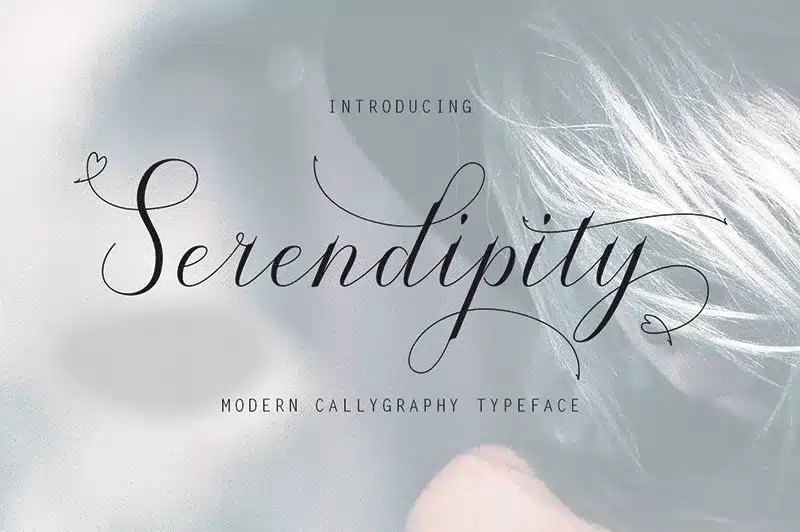
Serendipity เป็นฟอนต์ภาษาอังกฤษที่มีเสน่ห์ด้วยลายเส้นที่นุ่มนวลและเรียบง่าย การออกแบบที่เน้นความสบายตาและความเป็นธรรมชาติ ทำให้เหมาะกับงานออกแบบที่ต้องการความผ่อนคลายและความสบาย ๆ เช่น ร้านสปา ผลิตภัณฑ์บำรุงผิว หรือร้านอาหารเพื่อสุขภาพ
2. Honeydays
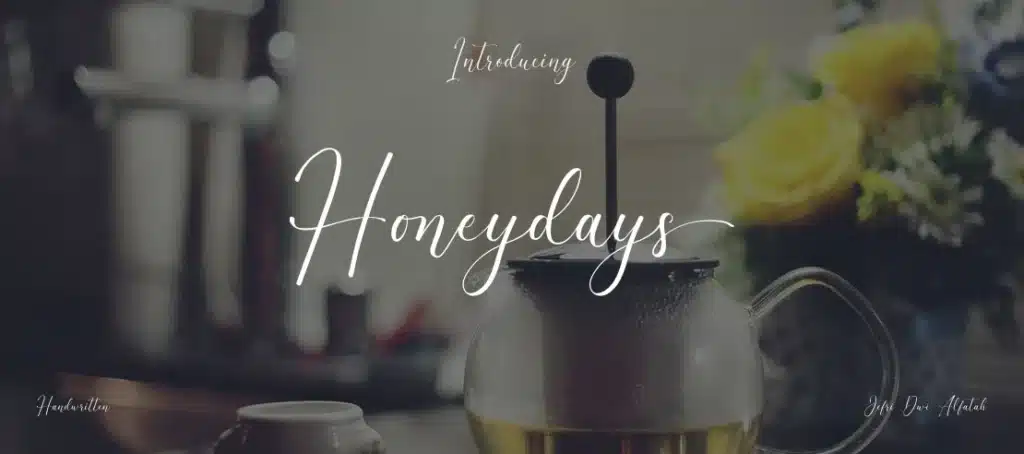
Honeydays เป็นฟอนต์ภาษาอังกฤษแบบ Calligraphy ที่มีความอ่อนหวานและสง่างาม โดดเด่นด้วยลายเส้นที่บางเบาและลื่นไหล สร้างความรู้สึกอบอุ่นและเป็นกันเอง เหมาะสำหรับงานออกแบบที่ต้องการสื่อถึงความรักและความอ่อนโยน เช่น การ์ดแต่งงาน การ์ดอวยพร หรือโลโก้ร้านดอกไม้
3. Butler
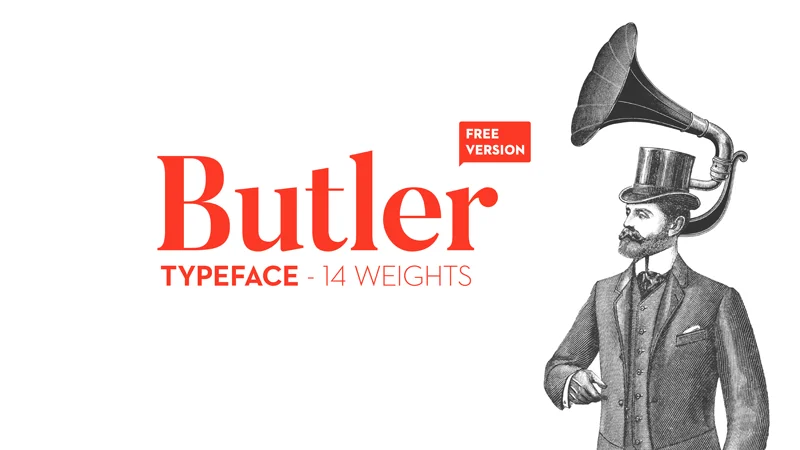
Butler เป็นฟอนต์อังกฤษที่นำเสนอความเรียบหรูผ่านการออกแบบสไตล์ Modern Serif ที่มีความสมดุลระหว่างความคลาสสิกและความร่วมสมัย ด้วยลายเส้นที่คมชัดและมีเอกลักษณ์ ทำให้เหมาะกับการใช้งานในหลากหลายรูปแบบ โดยเฉพาะงานที่ต้องการความน่าเชื่อถือและความเป็นมืออาชีพ
4. Pacifico
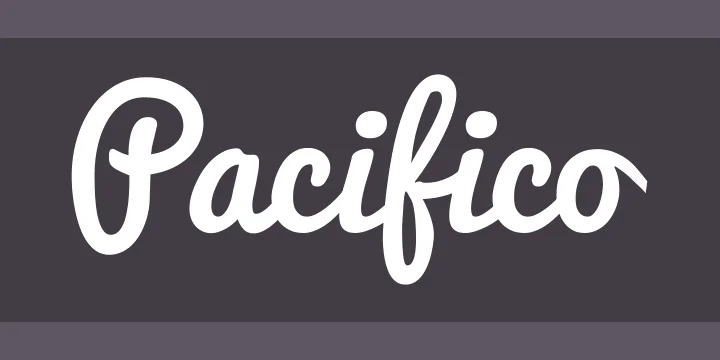
Pacifico เป็นฟอนต์อังกฤษที่ได้รับแรงบันดาลใจจากการเขียนด้วยพู่กันแบบย้อนยุค มาพร้อมกับความสนุกสนานและมีชีวิตชีวา ด้วยลายเส้นที่หนาแน่นและมีจังหวะที่สนุก เหมาะสำหรับงานออกแบบที่ต้องการความสดใสและความเป็นกันเอง เช่น ร้านอาหาร คาเฟ่ หรือธุรกิจท่องเที่ยว
5. Peich Typeface
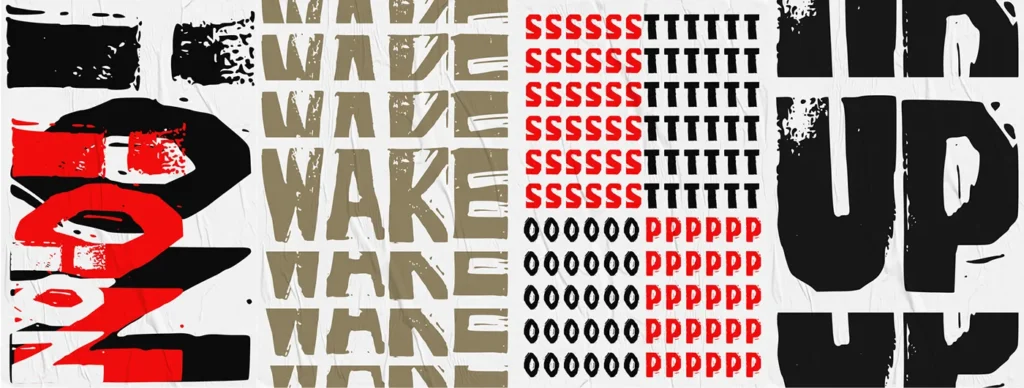
Peich Typeface เป็นฟอนต์ภาษาอังกฤษที่สร้างความโดดเด่นด้วยความหนาและความแข็งแกร่งของตัวอักษร ผสมผสานกลิ่นอายความวินเทจเข้ากับความทันสมัยได้อย่างลงตัว เหมาะสำหรับงานออกแบบที่ต้องการสื่อถึงความแข็งแกร่งและความมั่นคง เช่น โลโก้แบรนด์สปอร์ต ป้ายโฆษณา หรือแพ็กเกจจิงสินค้าสำหรับผู้ชาย
6. Sacramento
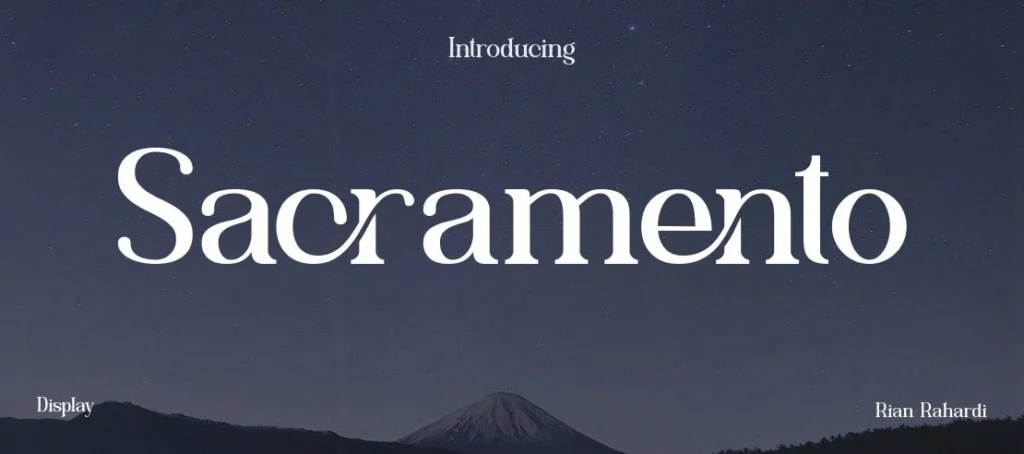
Sacramento ฟอนต์ภาษาอังกฤษตัวเขียนที่ได้แรงบันดาลใจจากการเขียนด้วยลายมือแบบคลาสสิกยุค 50-60 ผสมผสานความสวยงามของลายเส้นที่ลื่นไหลเข้ากับความเป็นธรรมชาติได้อย่างลงตัว เหมาะสำหรับงานออกแบบที่ต้องการความอ่อนช้อยและความเป็นศิลปะ เช่น งานแต่งงาน โลโก้ร้านดอกไม้ หรือการเขียนการ์ดอวยพร
7. Hello Night
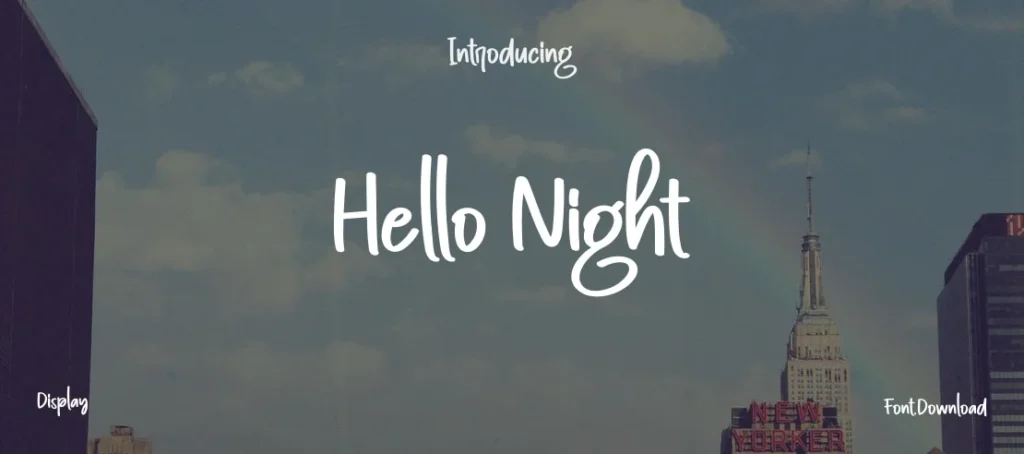
Hello Night เป็นฟอนต์อังกฤษตัวเขียนที่ผสมผสานความวินเทจเข้ากับความทันสมัยได้อย่างลงตัว ด้วยลายเส้นที่มีความพลิ้วไหวและสง่างาม เหมาะสำหรับงานออกแบบที่ต้องการความคลาสสิกแต่ไม่ดูเชย เช่น แพ็กเกจจิงสินค้าพรีเมียม หรือการ์ดเชิญร่วมงานต่าง ๆ
8. CLATTERING
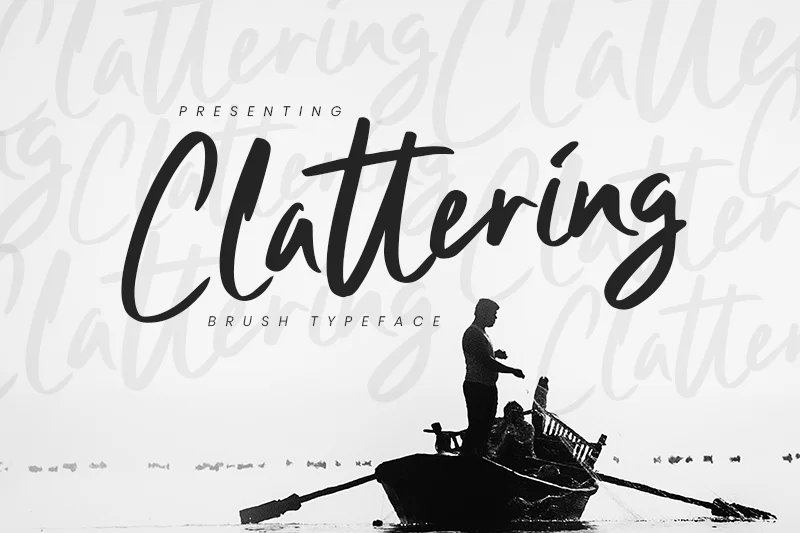
CLATTERING เป็นฟอนต์ภาษาอังกฤษสไตล์ Brush Script ที่โดดเด่นด้วยลายเส้นแบบสีน้ำที่ดูเป็นธรรมชาติและมีชีวิตชีวา ให้ความรู้สึกศิลปะและความคิดสร้างสรรค์ผ่านการไล่น้ำหนักของเส้นที่แตกต่างกัน เหมาะสำหรับงานออกแบบที่ต้องการความเป็นศิลปะ เช่น แกลเลอรี่ ร้านกาแฟ หรือสตูดิโอออกแบบ
9. Wild Youth
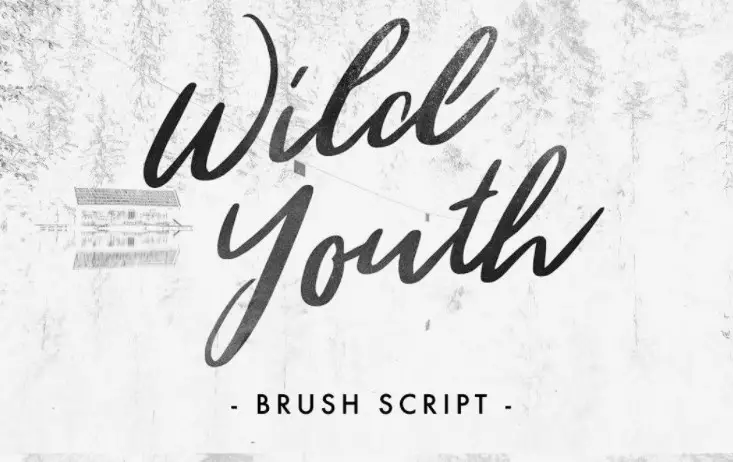
Wild Youth ฟอนต์อังกฤษที่ได้รับแรงบันดาลใจจากธรรมชาติและการผจญภัย สะท้อนผ่านลายเส้นที่ดูเป็นธรรมชาติแต่แฝงความเท่และทันสมัย เหมาะสำหรับแบรนด์ที่ต้องการสื่อถึงความเป็นออร์แกนิค อิสระ และการใช้ชีวิตกลางแจ้ง ไม่ว่าจะเป็นร้านอาหารเพื่อสุขภาพ ผลิตภัณฑ์ออร์แกนิค หรืออุปกรณ์แคมปิ้งก็ตาม
10. Lato
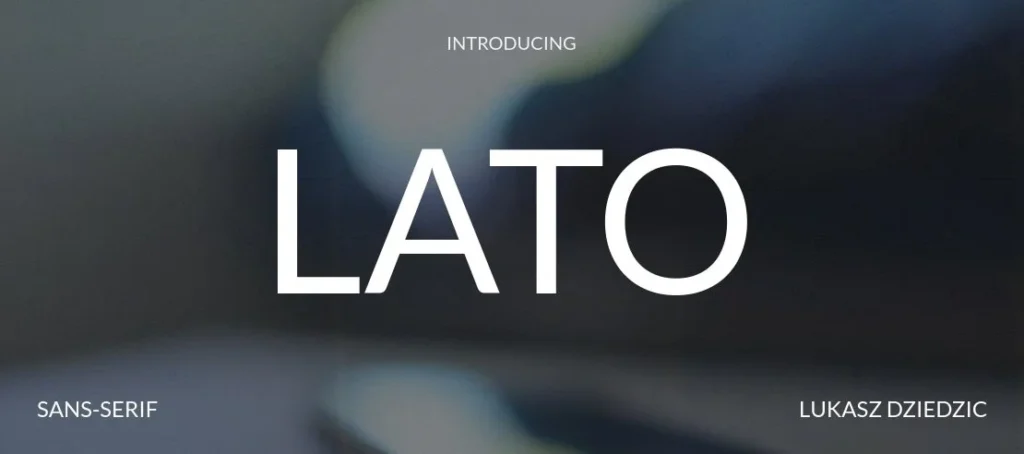
Lato ฟอนต์ภาษาอังกฤษสไตล์ Sans Serif ที่มีทั้งความเรียบง่ายและความทันสมัยประกอบกันได้อย่างลงตัว ด้วยลายเส้นที่สะอาดตาและมีความสมดุล ทำให้อ่านง่ายและดูเป็นมิตร เหมาะสำหรับการใช้งานทั้งในรูปแบบหัวเรื่องและเนื้อหา โดยเฉพาะงานออกแบบเว็บไซต์ แอปพลิเคชัน หรือสื่อดิจิทัลที่ต้องการความเป็นมืออาชีพ
11. Playfair Display
Playfair Display ฟอนต์ภาษาอังกฤษสไตล์ Serif ที่ผสมผสานความคมชัดและความนุ่มนวลได้อย่างลงตัว ด้วยการออกแบบที่มีความแตกต่างของความหนาบางในแต่ละเส้น ทำให้ดูมีมิติและน่าสนใจ เหมาะสำหรับงานออกแบบที่ต้องการความหรูหราแบบคลาสสิก เช่น นิตยสาร หนังสือ หรือเว็บไซต์ของแบรนด์หรู
12. Party Confetti
Party Confetti เป็นฟอนต์อังกฤษที่มีเอกลักษณ์โดดเด่นด้วยความหนาและรูปทรงที่สนุกสนาน แต่ยังคงความชัดเจนและอ่านง่าย เหมาะสำหรับการออกแบบงานที่ต้องการสื่อถึงความสนุกและมีชีวิตชีวา เช่น โปสเตอร์งานอีเวนต์ โลโก้ร้านเกม หรือสื่อโฆษณาสำหรับเด็ก
13. Wild World
Wild World ฟอนต์อังกฤษสไตล์ไซเบอร์พังก์ที่สะท้อนความเป็นดิจิทัลและอนาคต ด้วยการออกแบบที่เน้นเส้นตรงและมุมแหลม สร้างความรู้สึกล้ำสมัยและก้าวล้ำ เหมาะสำหรับงานออกแบบที่เกี่ยวข้องกับเทคโนโลยี เกม หรือธุรกิจสตาร์ตอัป โดยเฉพาะสื่อดิจิทัลที่ต้องการความแปลกใหม่
14. Great Vibes
Great Vibes อีกหนึ่งฟอนต์ภาษาอังกฤษสวย ๆ แบบตัวเขียนที่โดดเด่นด้วยลายเส้นบางเฉียบและลื่นไหล สร้างความรู้สึกหรูหราและมีระดับ ด้วยการออกแบบที่ผสมผสานความคลาสสิกเข้ากับความร่วมสมัยได้อย่างลงตัว ทำให้เหมาะกับงานออกแบบที่ต้องการความสง่างาม เช่น การ์ดแต่งงาน แพ็กเกจจิงเครื่องสำอาง หรือโลโก้แบรนด์แฟชั่นระดับพรีเมียม
สรุปบทความ
สำหรับใครที่อยากให้คอนเทนต์ภาษาอังกฤษออกมาโดดเด่น สวยงาม และมีการคุมมู้ดแอนด์โทนได้ดี การเลือกรูปแบบฟอนต์ภาษาอังกฤษเป็นเรื่องที่ไม่ควรมองข้าม เพราะฟอนต์อังกฤษจะช่วยสื่ออารมณ์ความรู้สึกและทำให้กลุ่มเป้าหมายรู้สึกอินไปกับคอนเทนต์มากยิ่งขึ้น และทั้งหมดนี้ก็คือ 20 ฟอนต์ภาษาอังกฤษสวย ๆ ที่เราคัดเลือกมาให้ สามารถดาวน์โหลดผ่านลิงก์ที่แนบและนำไปใช้สร้างคอนเทนต์ได้เลย! ทั้งนี้ อย่าลืมเช็กสักนิดว่าฟอนต์ภาษาอังกฤษที่เราสนใจนั้นอนุญาตการใช้งานแบบใด? เนื่องจากมีฟอนต์ที่ระบุให้ใช้งานเฉพาะผลงานส่วนตัวอยู่นั่นเอง